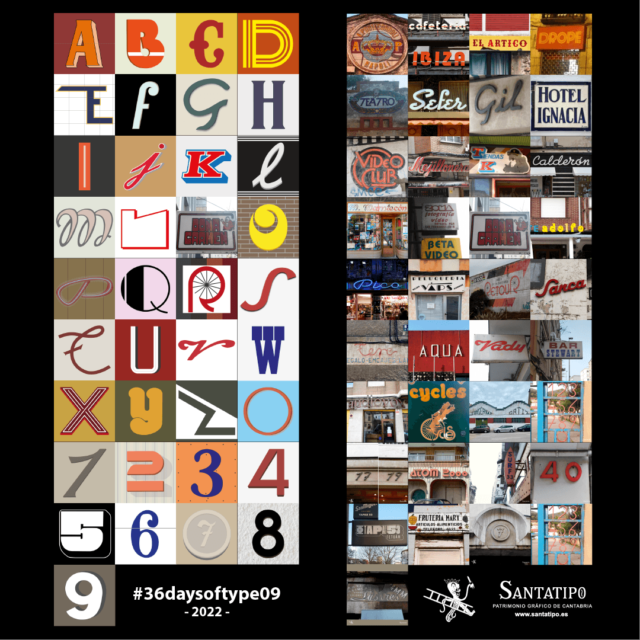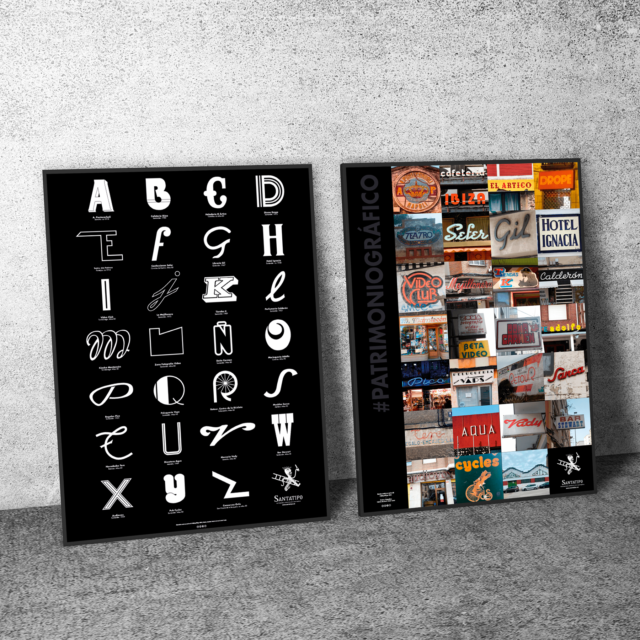
Poster 36 Days Of Type’22
Este nuevo poster, surge con motivo de la iniciativa «36 days of Type» en la que hemos participado sacando tipografías de la A a la Z, incluyendo número, basadas en parte de los rótulos cántabros que hemos ido documentando a lo largo de estos años, y que hemos publicado durante estos 36 últimos días en nuestras redes sociales. Lógicamente, no están todos los que son, ni son todos los que están. Es una pequeña muestra de nuestro paisaje visual y tipográfico.
Sobre 36 days of type
Esta maravillosa iniciativa surgió en 2014 de la mano de dos diseñadores gráficos barceloneses, Nina Sans y Rafa Goicochea, en la que invitaron a diseñadores, artistas y creativos a publicar durante ese tiempo su interpretación del abecedario, creando un festival tipográfico durante estos años.